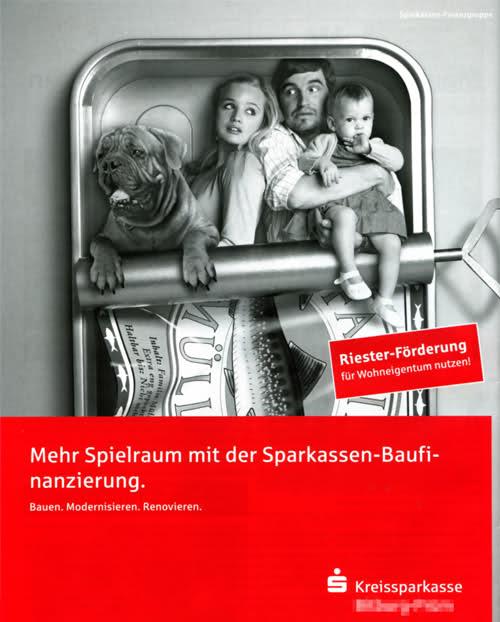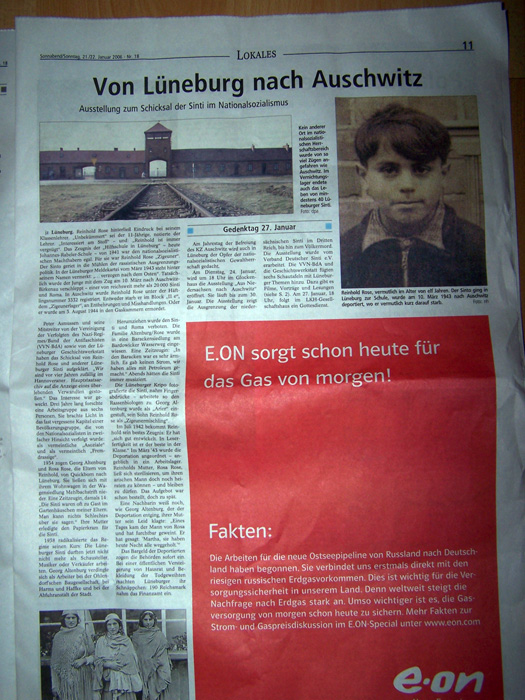
Mehr Spielraum mit dem gelobten automatischen Umbruch!
»Auto-Korrektur, Auto-Silbentrennung, Drauflostippen, Feierabend.« – auch, wenn’s gerade mal fünf Worte bzw. zwei Zeilen sind. :cry:
Dass außerdem der Wauwau ein bis zwei Nummern zu groß geraten ist, ist ’ne andere Geschichte … ;)
Schon klar, aber es ist halt doch ärgerlich, daß die mit Sachen durchkommen, die man jedem Schriftsetzerlehrling um die Ohren hauen würde.
… und das machen richtig teure Agenturen.
nö, das machen oft Kleinst-Klitschen für die örtliche Sparkasse. Das Motiv und die Textvorgabe kommen von der Spka oder der "teuren Agentur", auf die Vor-Ort-Formate wird das dann von irgendjemandem umgesetzt.
nö, das machen oft Kleinst-Klitschen für die örtliche Sparkasse. […]
Ja, das trifft hier wohl zu, ist aus einer eher ländlichen Region.
Solche tollen Schriftzüge machen sicher auch ganz tolle Agenturen mit ganz viel Gespür ...
Ich hoffe wirklich stark, dass die Anzeige inhouse gesetzt wurde. Alles andere wäre wirklich schlimm. :)
Wirklich schlimm finde ich eher solche Fehler:eongasvonmorgen3mz.jpg[/attachment:pijhqgs4]
Ach wo, eher hatte da eon eine Drittelseite reserviert und der Layouter hat einfach den Platz blankgeschlagen und die Seite fertiggemacht. Kurz vor Redaktionsschluß werden dann die Anzeigendaten eingetrudelt sein und irgendwer hat die noch schnell plaziert, ohne redaktionellen Inhalt gegen Anzeigentext abzugleichen (was man ja normalerweise im hektischen Zeitungsgeschäft wohl auch nicht tut). Ich denke nicht, daß das jemand bewußt gemacht hat.
(Oder das ganze Ding [Quelle?] ist vielleicht gephotoshopt.)
nö, das ist leider wirklich passiert. Eine von ca. 210 Trillionen Quellen.